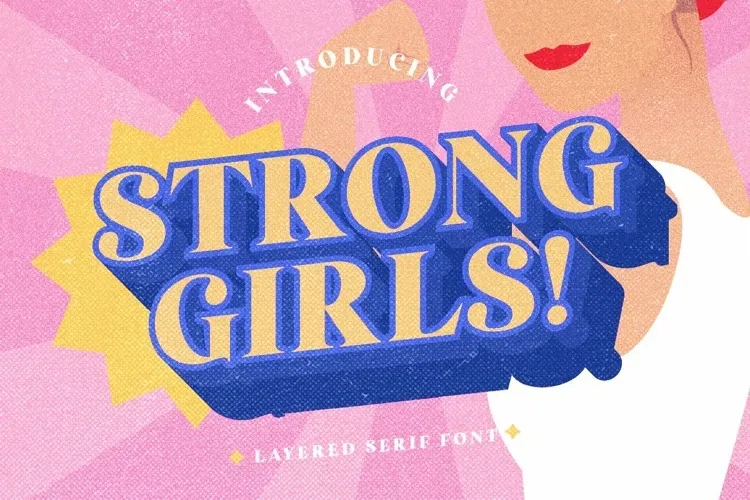
Strong Girls Font
Esta é uma fonte serif única e elegante criada pelo designer Saridezra. É uma fonte com camadas que inclui quatro tipos diferentes: regular, contorno, embutida e extrutura longa. Como outras fontes com camadas, você pode montar todos estilos em um texto para criar um design tridimensional. Esta fonte é adequada para diversos fins como panos de propaganda, adesivos, design vintage ou qualquer outro lugar onde desejar dar vida a suas ideias gráficas de uma maneira moderna e sofisticada. Através da personalização em seu texto com diferentes estilos dessa fonte multilayer, você pode transformar qualquer design em algo que brilha com um toque de profundidade. Além disso, a fonte Strong Girls está disponível para múltiplas línguas, tornando-a uma opção versátil e flexível. Sua simplicidade e elegância fazem dela a escolha perfeita para aqueles que procuram personalizar suas criações de forma criativa e sofisticada.